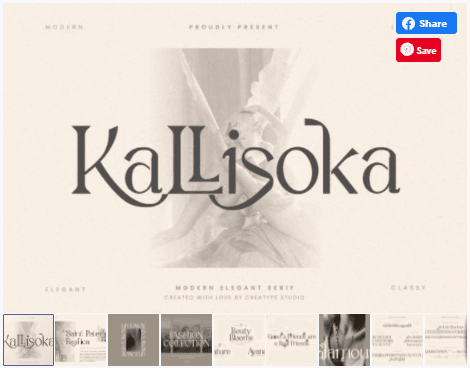
Kallisoka Font
Kallisoka - это современный жирный шрифт с засечками. Этот шрифт закодирован в кодировке PUA, что означает, что вы можете легко получить доступ ко всем глифам и штрихам! Добавьте его к своим любимым творениям и позвольте себе удивиться полученному результату.